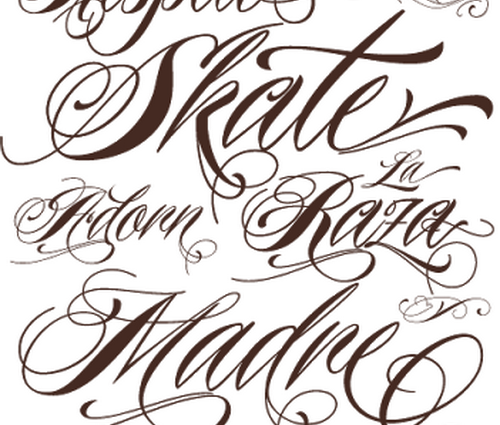
Все больше и больше среди молодежи становятся популярными татуировки, особенно надписи. Для тату с надписями самое главное правильно подойти к выбору шрифта, ведь их существует очень много. Давайте рассмотрим самые распространенные и популярные из них.
Шрифты для татуировок: общие сведения
Люди, которые решаются на такой шаг, как сделать себе татуировку, считаются современными и смелыми. Они не боятся в старости выглядеть странно. Татуировки могут быть изображены в виде рисунка и надписи, где каждая композиция имеет свое обозначение. Перед тем, как делать тату, главное учитывать местоположение рисунка, стиль написания, размер слов. Первая буква должна быть заглавной, выделенной цветом, с наклоном или в определенном стиле. Множество вариантов шрифта дают возможность сделать надпись более оригинальной и красивой.
Особенность шрифта для мужских и женских татуировок
Большинство голливудских звезд любят делать на своем теле тату в виде надписей.
Дизайн и выбор языка для татуировки
Английский язык считается мировым, потому для татуировок он является идеальным вариантом и пользуется большим спросом. При выборе татуировки стоит учитывать, будет ли это каллиграфический шрифт, шрифт с вензелями, единое слово или определенная фраза. При нанесении надписи стоит согласовать с мастером дизайн заглавной буквы, ведь не каждая буква может смотреться идеально. Мастер может предложить дополнить вашу надпись определенными элементами либо цветом. Для подбора тату можно воспользоваться услугой интернета либо тату-салона. Чтобы можно было передать другим людям смысл своей надписи, нужно учитывать несколько правил: легкая читаемость и исключение мелкого шрифта.
Основные виды шрифтов для татуировок
В тату-салонах могут предложить каталоги с эскизами шрифтов для татуировок. Более современные салоны, где можно сделать тату, предпочитают такие шрифты, как готический, граффити, каллиграфический, западный.
Готический шрифт
Музыкальные коллективы используют такой шрифт для нанесения своих логотипов. Такой шрифт может быть простым и сложным. Именно от этого будет зависеть то, с какой легкостью воспринимается и читается надпись.
Стиль граффити
Такой стиль подразумевает в себе смешение топографического шрифта и иллюстраций. Не каждый мастер татуировок сможет выполнить ваш заказ. Этот стиль пришел к нам с улиц.
Каллиграфические шрифты
В основном для нанесения надписи выбирают именно этот шрифт. Он более разборчив и понятен.
Не составит большого труда выбор знаков и букв, которые будут подходить для татуировки. Обычно классический шрифт используется для татуировок в виде старинной надписи, а простой – для тату надпись, сделанной «от руки».
Шрифт Западный
Такой шрифт татуировок можно встретить в основном в использовании у байкеров. Рассматривая тату с данным шрифтом, можно окунуться во времена Дикого Запада.
Популярные разновидности шрифтов для выполнения татуировок
Очень часто на практике используются следующие шрифты:
Шрифт рукописный
Этот шрифт традиционных татуировок основан на завитках и написании от руки. В этом формате обычно выполняются маленькие и заглавные буквы, а так же цифры.
Шрифт Aseina
Такой шрифт выполняется винтажным стилем. Благодаря сочетанию цифр, грифов и букв, такой способ дает необыкновенное ощущение элегантности.Шрифт November
Прекрасный стиль, который выполняется вручную и оцифровывается для красивого дизайна.
Такой шрифт содержит цифры, буквы, а изумительное соединение букв придает потрясающий искусный эффект.
Машинописный шрифт
Уникальный, но в то же время совсем простой машинописный шрифт для татуировок. Он выполняется в стиле печатного классического начертания. Такой стиль содержит в себе буквы, цифры, а так же 187 замечательных грифов.
Шрифт Victoriandeco
«Рубленый» викторианский шрифт понятен и прост в использовании. Этот шрифт содержит в себе полный комплект необходимых букв с орнаментальными элементами для украшения татуировки.
Шрифт Stay High
Современный шрифт, созданный на основе уличной росписи. Такой шрифт выполнен в «диком формате», но содержит в себе все нужные символы. Больше всего такой шрифт подходит для любителей граффити.
Шрифт Bekelakar
Такой шрифт подходит для тех, кто обожает готический дизайн и металл, а также ужасы. Этот шрифт выполняется в форме заглавных и прописных букв, с полным комплектом знаков препинания и цифр.
Stiquez шрифт
Такой вид более подходит для логотипов. Также его можно использовать в дизайне тату. Этот уникальный с засечками шрифт выполняется в крутом ретро дизайне.
Шрифт Rude Cookie
Этот рукописный шрифт уникален своим характером, содержащим в себе два вида шрифтов. Эти шрифты идеально дополняют друг друга, что помогает выполнению интересного тату-дизайна.
Шрифт Honeycomb
Восхитительный шрифт, наполненный игривыми и причудливыми элементами. Такой стиль создан на неровной основе, мазками кисти, от тонких к широким.
Как правильно выбрать шрифт для нанесения татуировки?
Для нанесения татуировки в виде надписи на свое тело можно заранее подобрать шрифт. С помощью компьютерных программ это можно сделать очень просто. Даже при помощи социальной сети можно подобрать нужный шрифт, написав фразу или слово. Для того чтобы надпись смотрелась более интереснее и гармоничней, её наносят в области запястья, поясницы или щиколотки.
Шрифт Bekelakar
Если вы обожаете ужасы, метал или готический дизайн, вы определённо полюбите этот шрифт. Этот шрифт доступен в форме прописных и заглавных букв, с полным набором букв, цифр и базовых знаков препинания.
Шрифт Dramaga
Создайте драму с этим сумасшедшим шрифтом Dramaga. Созданный по мотивом дизайна постхардкорной группы, этот шрифт пронизан глубокой готической атмосферой с уникальными угловатыми акцентами. Скачайте этот шрифт, чтобы применить его в своей следующей татуировке.
Шрифт Sadis